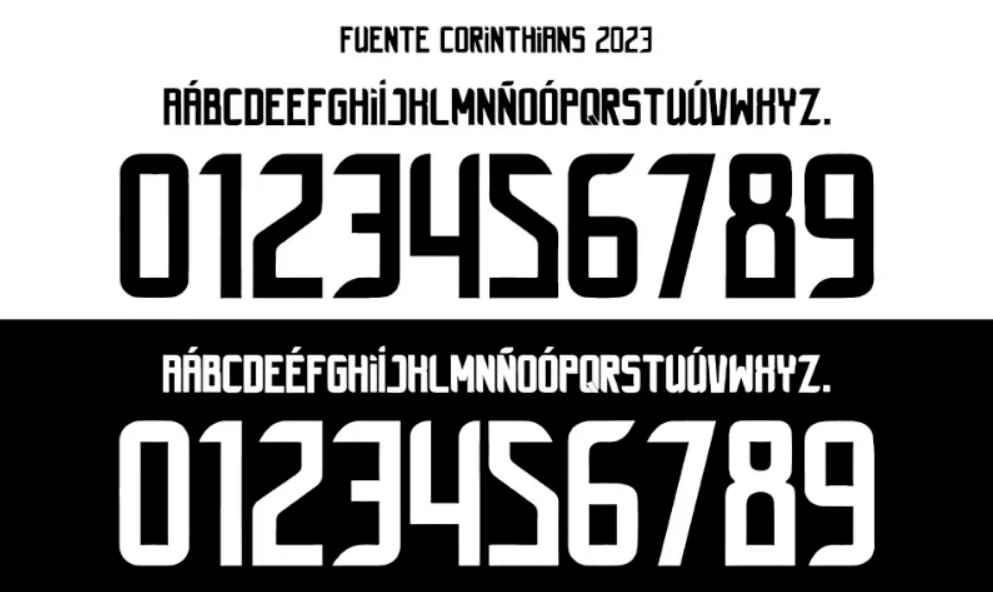
Esta é a tipografia utilizada pelo Timão durante a temporada de 2023, vestindo os craques nos desafios do Brasileirão, Copa do Brasil e Libertadores. Desenvolvida em parceria com a Nike, esta fonte complementa perfeitamente o design dos uniformes “Home” (o clássico branco) e “Away” (o listrado vertical), mantendo a tradição alvinegra com um toque de modernidade.
Estilo Visual e Identidade
A tipografia de 2023 do Corinthians segue a linha de design global da Nike, mas com ajustes que garantem visibilidade e impacto.
Diferente de temporadas anteriores que apostaram em estilos “rabiscados” ou referências históricas muito específicas (como a fonte de 2012), a versão 2023 aposta no minimalismo geométrico.
- Legibilidade: Os números são robustos e de fácil leitura à distância, essenciais para a identificação em campo e na TV.
- Geometria: Apresenta cortes retos e ângulos internos suaves, transmitindo uma sensação de tecnologia e performance.
- Aplicação: Fica incrível tanto na cor preta (para a camisa branca) quanto na branca com bordas (para a camisa listrada ou preta de goleiro).
É a fonte ideal para estampar nomes de ídolos daquela temporada, como Renato Augusto, Yuri Alberto e Róger Guedes, ou para criar camisas personalizadas para torcidas organizadas e eventos de várzea.
- Conteúdo: Alfabeto completo (caixa alta) e numeração oficial (0-9).